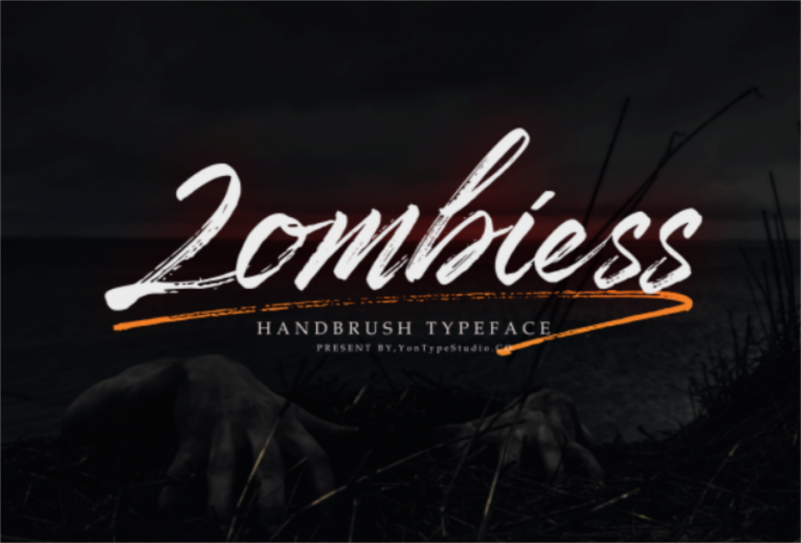
Zombies Hand Brush font – Download Grátis
Introduzimos Zombies Hand Brush Font, uma elegante e rusticamente amigável fonte escrita a mão que irá enriquecer seu design com uma personalidade única. Inspirada nos traços ásperos e distintivos das mãos de zombies, esta fonte é perfeita para o mundo do branding, designs de aparelhos domésticos ou embalagens de produtos. Seja você um criador de marca ou designer gráfico, Zombies Hand Brush é uma opção ideal para adicionar um toque único a qualquer imagem de fundo. Através de seu design fluido e rápido-drenado, você pode garantir que esta fonte se torne uma peça chave em suas criações visuais. Caso queira experimentar o charme desta fonte para si mesmo, não hesite em baixá-la agora. Zombies Hand Brush Font é perfeita para qualquer projeto de design gráfico que você precise.